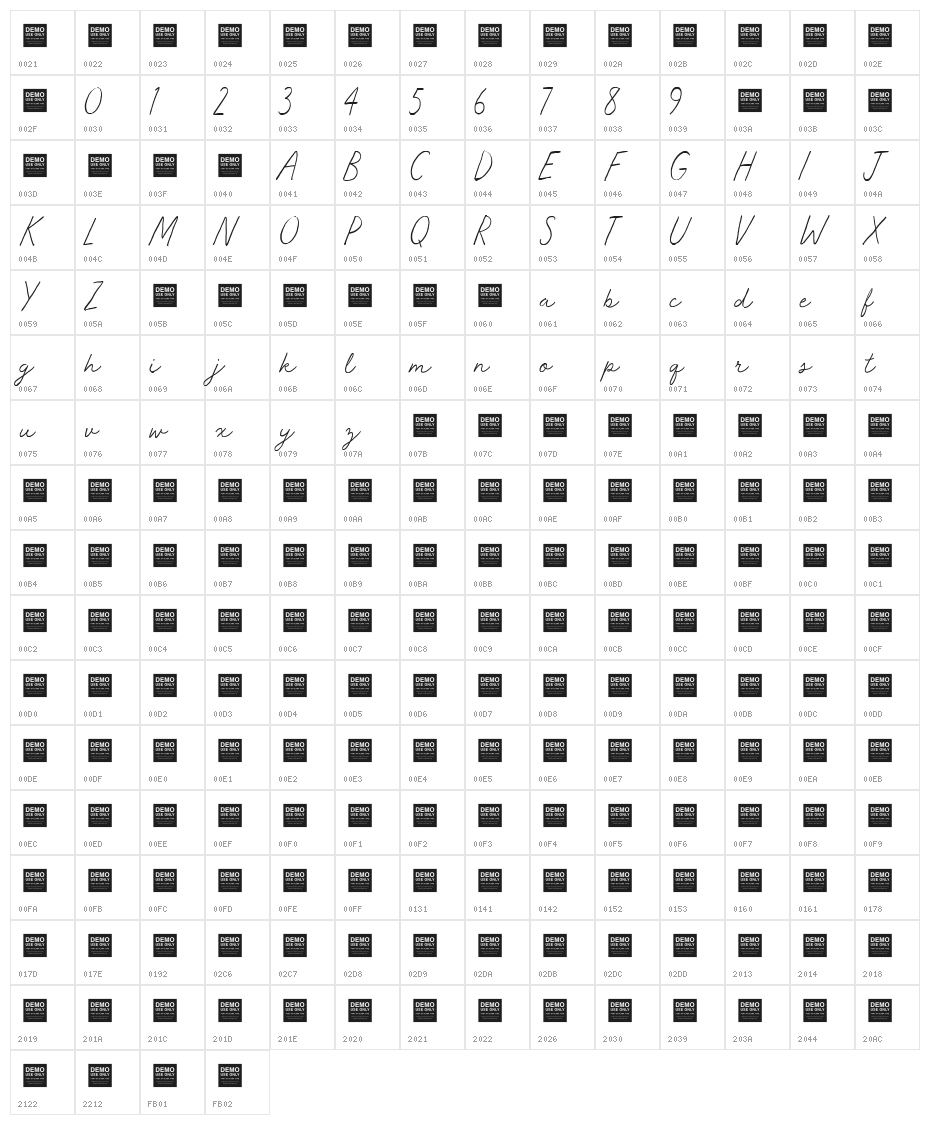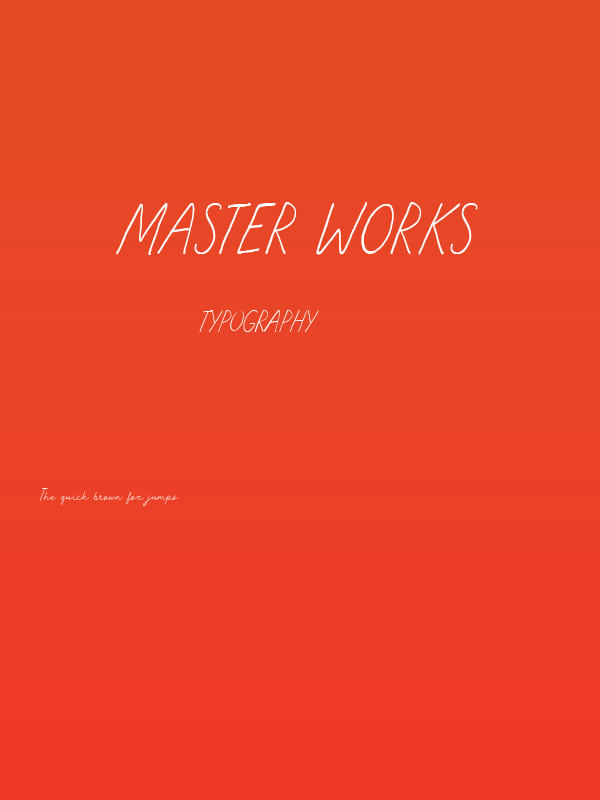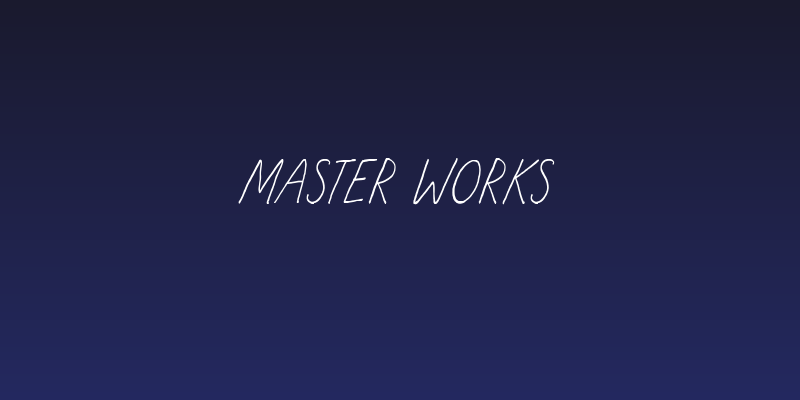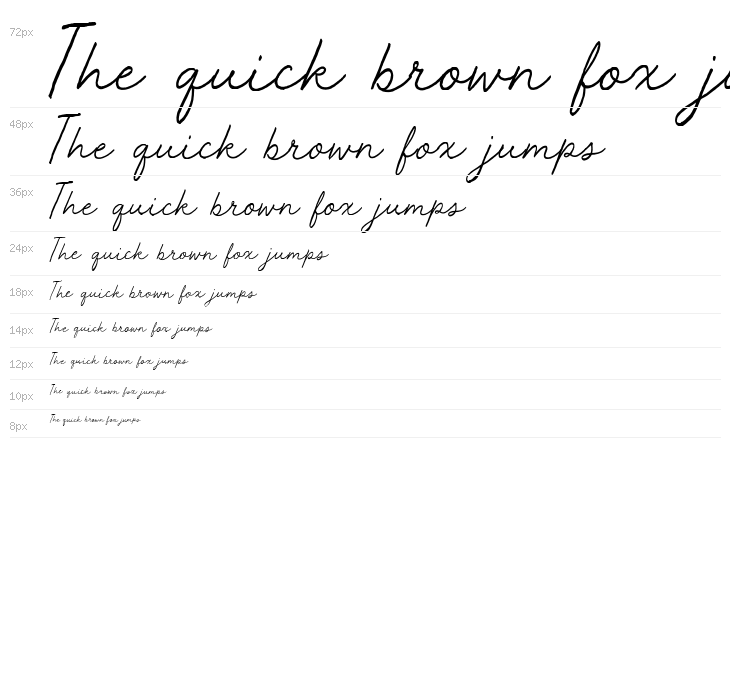
Master Works Font
✎ Handwritten
| 名称 | Master Works |
| 分类 | Handwritten |
| 斜体 | Yes |
| 整体风格 | Casual, Elegant |
| 使用场景 | Logos, Invitations, Personal notes |
| 推荐项目 | Ideal for personal invitations, greeting cards, and branding that requires a personal touch. |